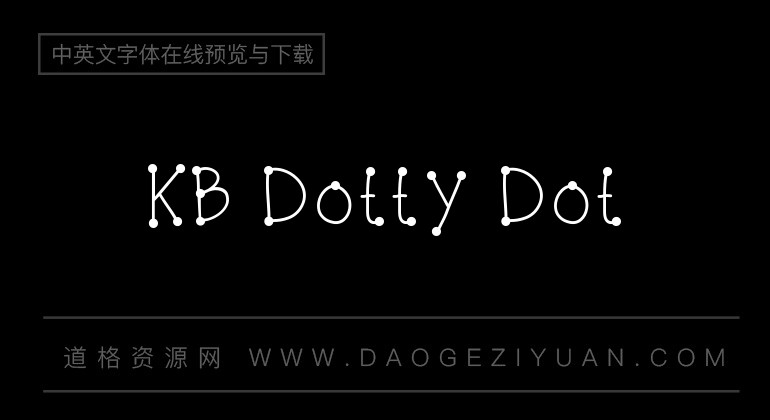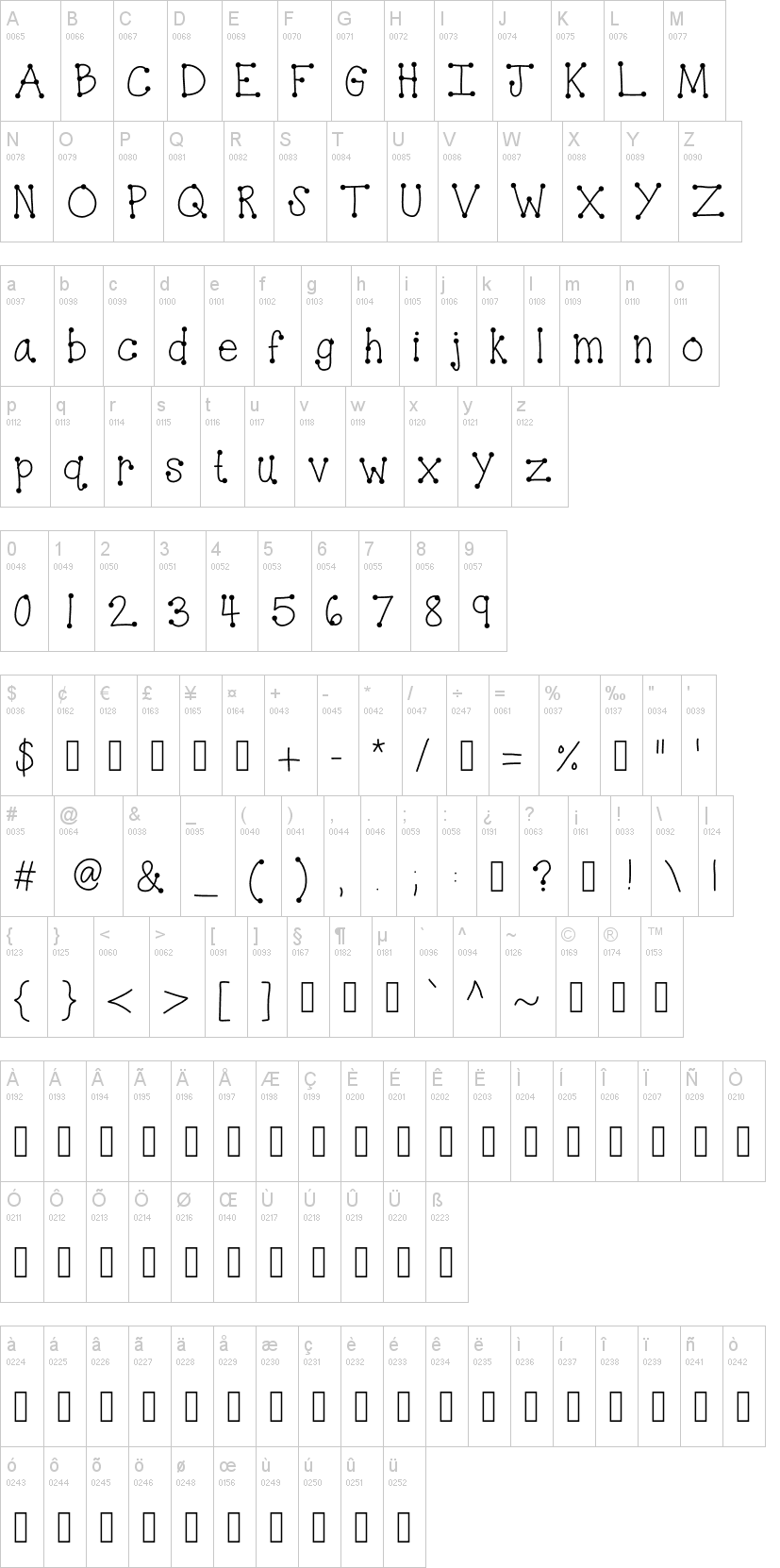
KB Dotty Dot
KB Dotty Dot 是一款经典的脚本字体,由 Kōichi Beppu 和 TypeBank 共同开发。它是一款带有点状风格的字体,具有优雅的外观和柔和的曲线,可以为您的设计带来细致的细节和温柔的氛围。KB Dotty Dot 字体的特点是它的字体设计具有优雅的外观和柔和的曲线,可以为您的设计带来细致的细节和温柔的氛围。它可以用于商业和个人设计,是一款多用途字体。
KB Dotty Dot是一款非常不错的手写艺术字体,具有很好的视觉感,适合于文化类的宣传设计、商业类品牌的广告和产品包装设计以及个性化文字排版等较多场景。
KB Dotty Dot字符映射图